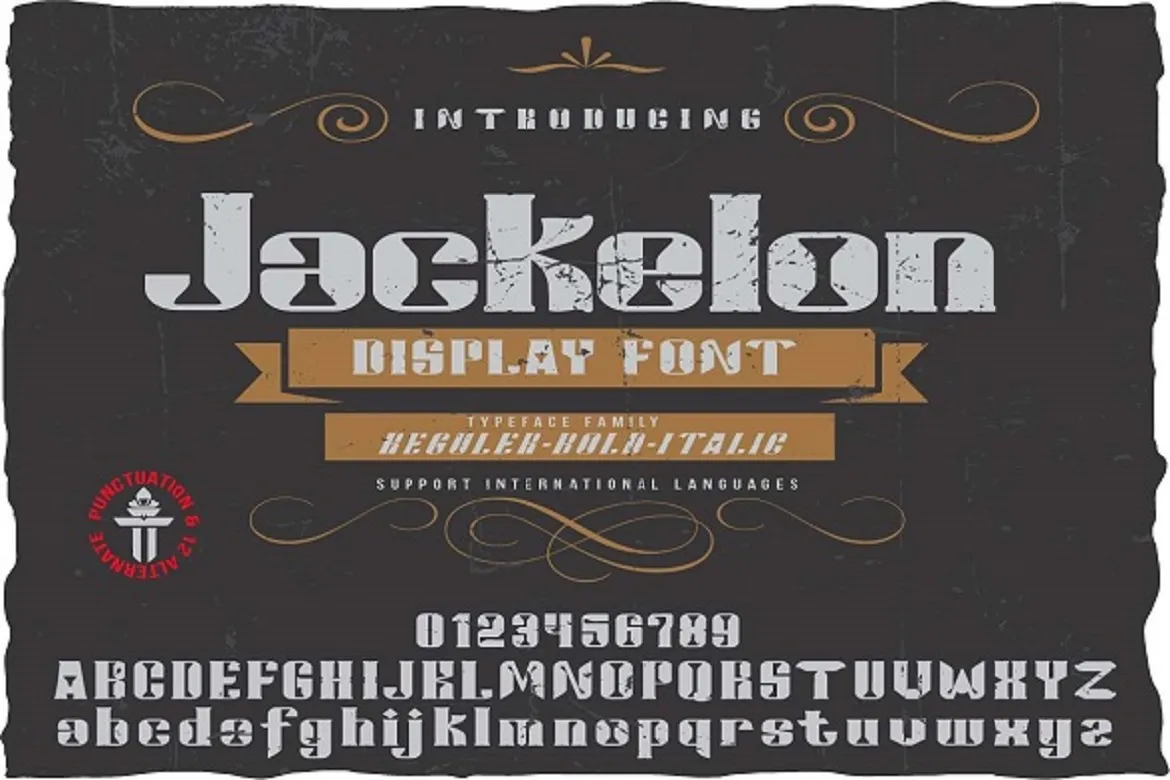
Jackelon Font – Fonte Grátis
Jackelon Font
Esta é uma fonte que exibe a elegância dos caracteres com uma característica especial para obter resultados impressionantes. O Jackelon é uma excelente opção para banners, fitos, jogos e rótulos. Nossas fontes foram projetadas especificamente fornecendo três opções de correntes, negrito e itálico. Esta fonte realmente ajuda você a criar projetos belos. Concebida pelo designer Anton Septiawan, o Jackelon é perfeito para ambientes visuais dinâmicos e criativos, permitindo que você personalize visualmente seus materiais em um nível avançado. Seja para a criação de elementos de jogos impressionantes ou rótulos de alimentos modernos e chamativos, essa fonte está pronta para transformar qualquer projeto em algo realmente especial. Não perca tempo! Experimente o Jackelon Font agora e veja como ele pode revolucionar a maneira como você apresenta seus materiais visuais.
Designer: Anton septiawan